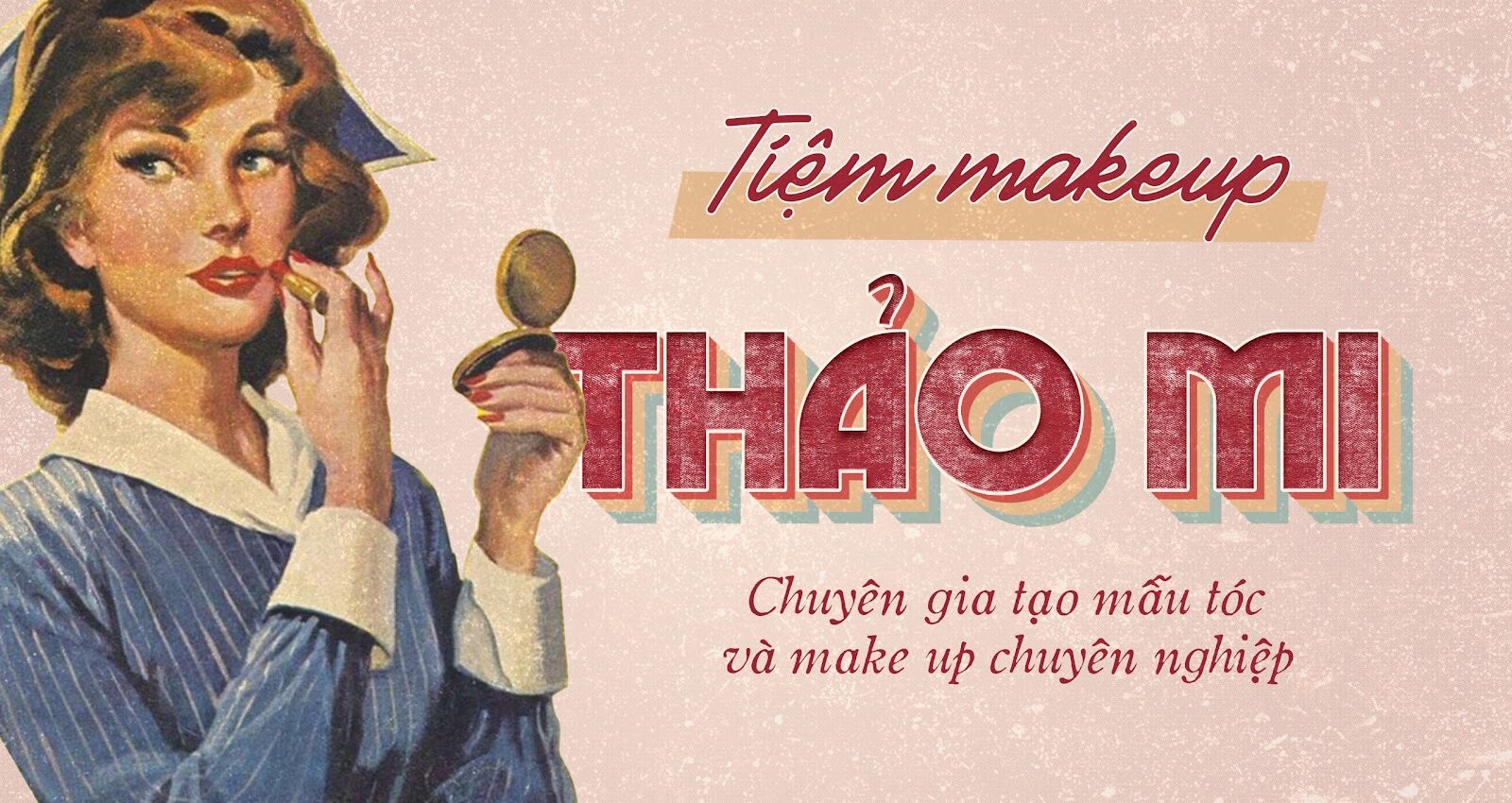
Font iCiel BCLodestone Free
Phân loại: Cá tính
Font iCiel BCLodestone là một font thuộc bộ font iCiel độc đáo thuộc dòng chữ kiểu cổ điển, mang phong cách mạnh mẽ và cá tính. Được thiết kế với các nét chữ cứng cáp, dày dặn và đậm chất retro, font iCiel BCLodestone thường được sử dụng trong các dự án thiết kế như logo, tiêu đề, banner hoặc các sản phẩm đòi hỏi sự nổi bật và ấn tượng. Font này không chỉ mang lại cảm giác cổ điển mà còn giúp tạo điểm nhấn mạnh mẽ cho bất kỳ thiết kế nào, đặc biệt phù hợp với những chủ đề mang tính cách mạng hoặc cổ điển hiện đại.